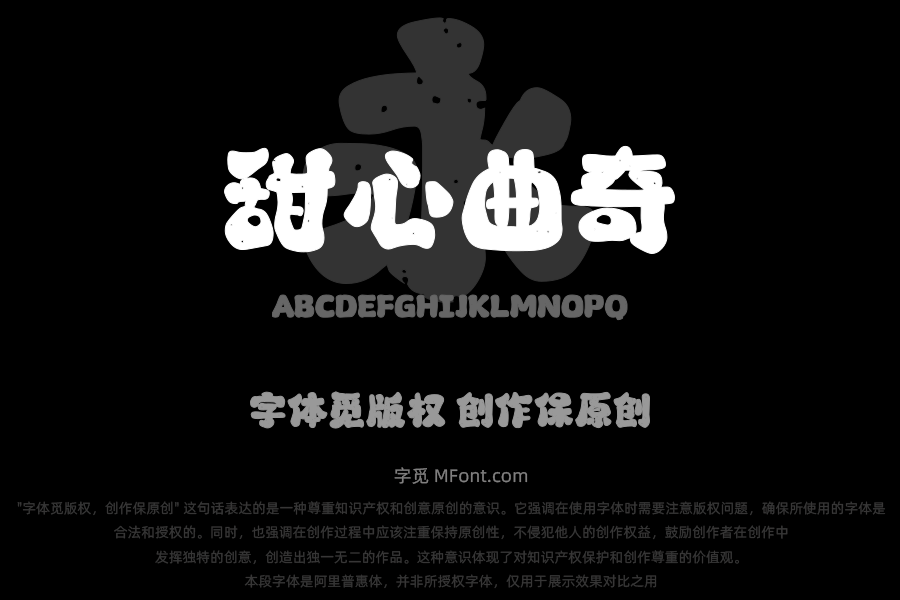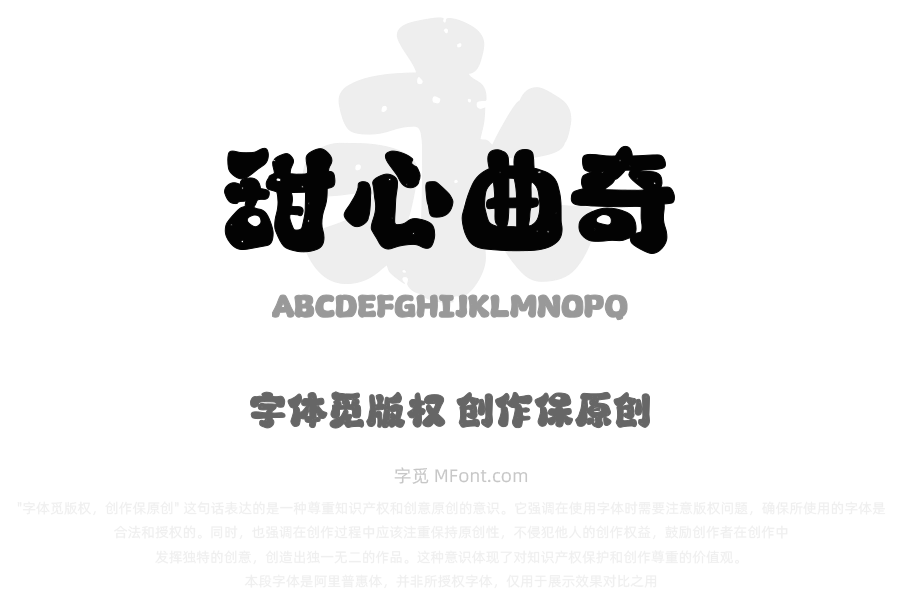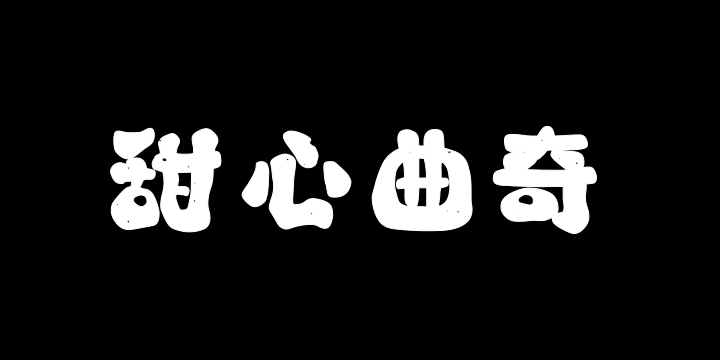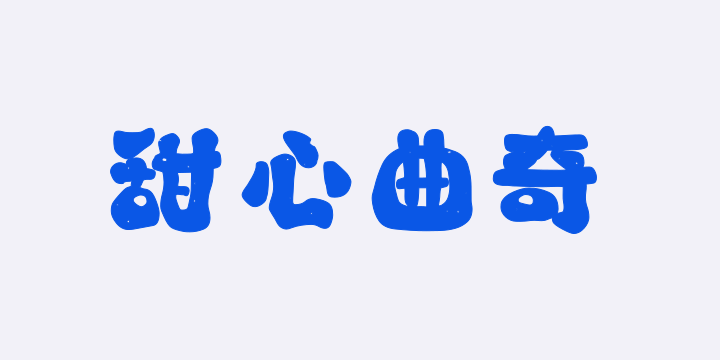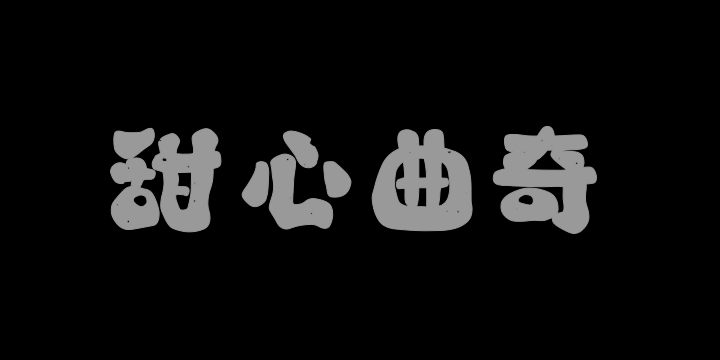
关于山海甜心曲奇W字体字库信息
字体全名: 山海甜心曲奇W
铸字厂: 山海字库
设计师: 山海字库
字体简介: 山海甜心曲奇,是一款卡通风字体,包含简繁汉字9169个。该字体是一款具有强劲视觉冲击力的粗体字体。字形粗大,充实填满整个字框。风格童趣,结构多变灵动,线条柔和。字形中融入手绘风元素及手绘镂空元素,宛如一个个曲奇饼干,造型生动有趣,具有灵活的适用性,天真俏皮又不失时尚感。
所属分类: 卡通